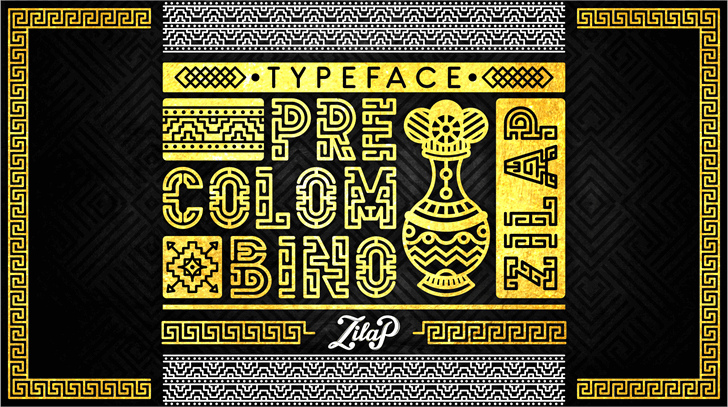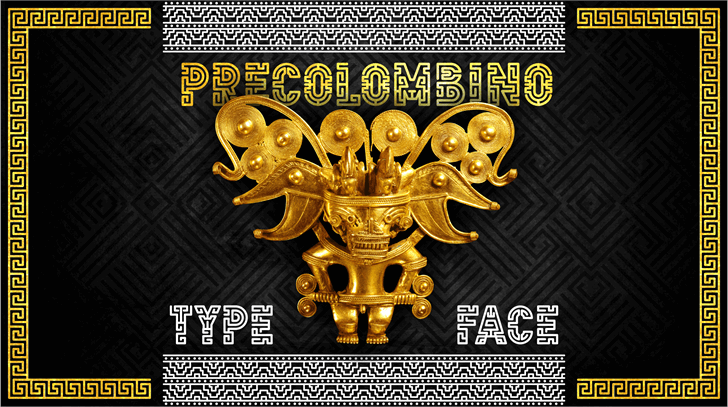
Zilap Precolombino Typeface
ZILAP PRECOLOMBINO – Una fuente que conceptualiza una época, una expresión cultural, una historia y sus tradiciones.
Este es el reconocimiento gráfico de toda una herencia cultural que visualmente representan a todo un país, “Colombia”.
Los símbolos están diseñados e inspirados en el concepto del arte de esa época